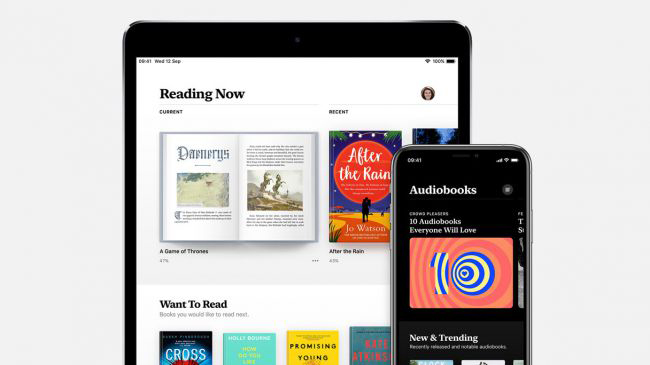
Il novo font free di Apple che non è poi tanto free!
Sono stati giorni impegnativi per i fan Apple. Alla sua conferenza WWDC 2019, non solo il gigante della tecnologia ha introdotto iOS 13 e lanciato un bellissimo nuovo Mac Pro con un cartellino del prezzo da mandare in bancarotta la maggior parte di noi, ma tra le news più succose per noi designer vi è anche quella di aver svelato un nuovo font di sistema.
Un elegante carattere serif chiamato”New York” è ora disponibile per il download gratuito (se hai bisogno di più caratteri complementari consulta la nostra raccolta dei migliori e dei font gratuiti qui). Disponibile in sei pesi e quattro dimensioni, New York è un antagonista del carattere sans-serif San Francisco disegnato da Antonio Cavedoni (che abbiamo avuto modo di intervistare qui). Il nuovo font prende il nome da un carattere tipografico serif di transizione creato dalla graphic designer Susan Kare nel 1983.
Tuttavia, i nostri fan grafici hanno notato che New York non è del tutto nuovo come suggerisce l’annuncio in pompa magna, poiché è apparsa sull’app Apple Books alla fine dello scorso anno.
Apple Books
Il carattere tipografico di Books vi sembra familiare?
[Immagine: Apple]